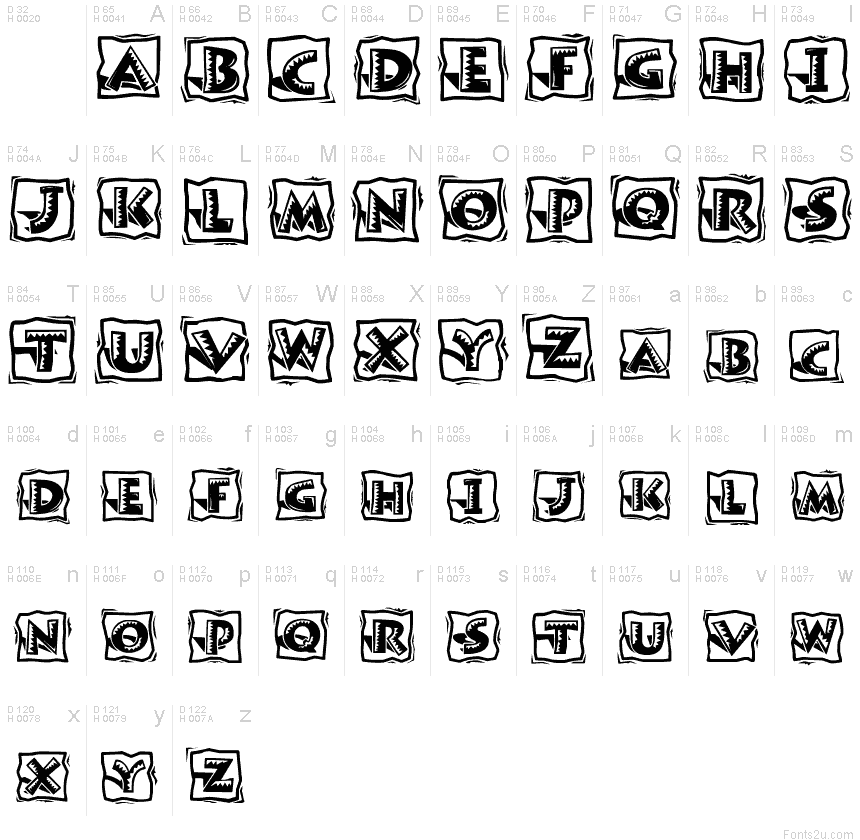
Ryp Fiesta B von Robyn Phillips ist eine kostenlose, mexikanisch inspirierte Displayschrift aus massiven, kantigen Großbuchstaben. Unregelmäßige Rahmen umgeben gekerbte Buchstaben mit Zickzack-Aussparungen.
Auf Fiesta-Plakaten und Restaurant-Speisekarten fungieren die eingerahmten Buchstaben sowohl als Text als auch als dekoratives Element. Dieselbe lebendige Gestaltung eignet sich für Lebensmittelverpackungen und Event-Merchandise, besonders in Kombination mit Papel Picado, handgemalten Schildern oder festlichen Bordürenmustern. All diese Einsatzbereiche teilen die Vorliebe für gerahmte Schriftzüge und kantige Ornamente.